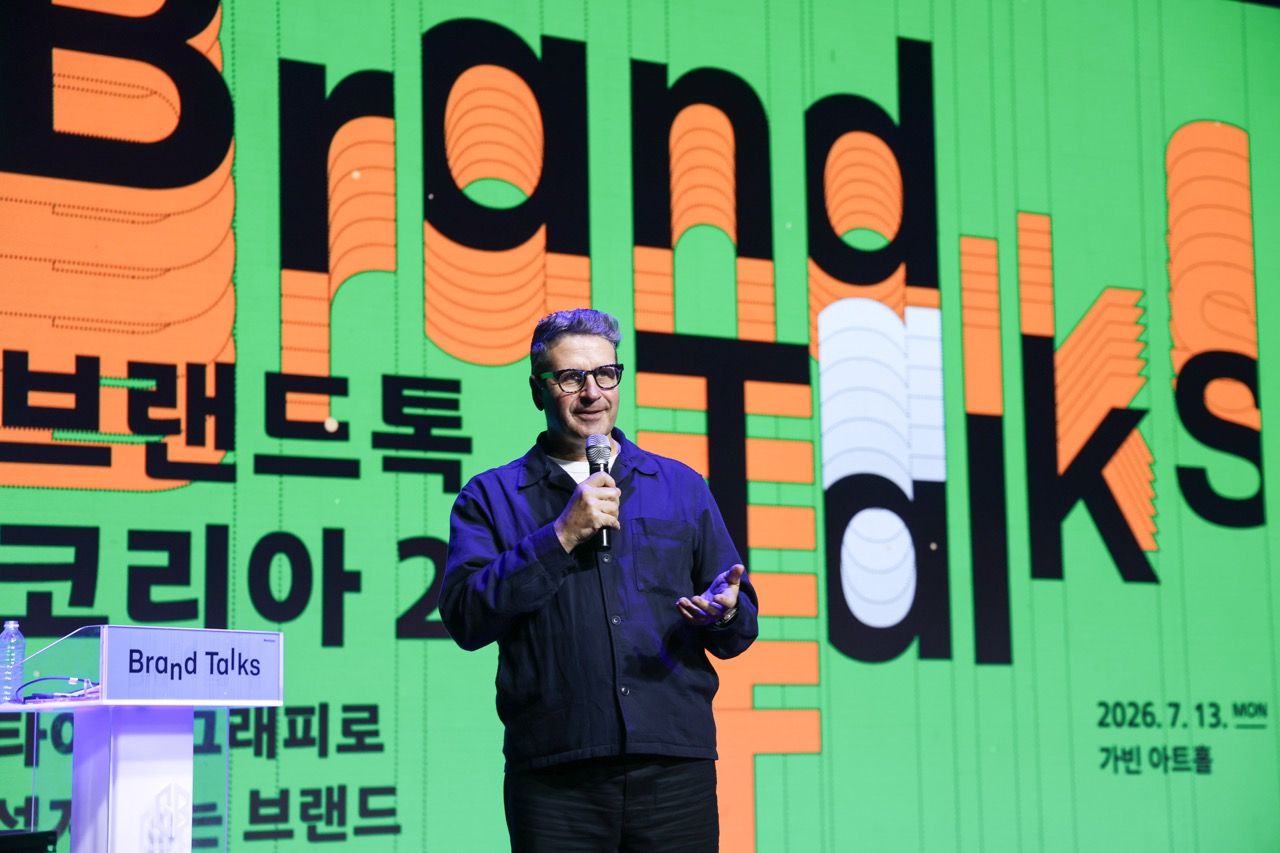
- 타이포그래피와 리브랜딩 사례 통해 브랜드 경험 설계의 방향 제시
모노타입은 지난 7월 13일 서울 가빈아트홀에서 개최한 ‘브랜드톡 코리아 2026(Brand Talks Korea 2026)’을 성황리에 마무리했다고 밝혔다.
올해로 3회째를 맞은 브랜드톡 코리아는 국내 브랜딩, 디자인, 마케팅 업계 관계자들과 타이포그래피의 가치와 가능성을 공유하기 위해 마련된 행사다. 올해 행사는 ‘타이포그래피로 설계하는 브랜드’를 주제로, 타이포그래피를 단순한 시각적 디자인 요소가 아닌 브랜드의 목소리와 경험을 만들고 지속시키는 핵심 시스템으로 조명했다.
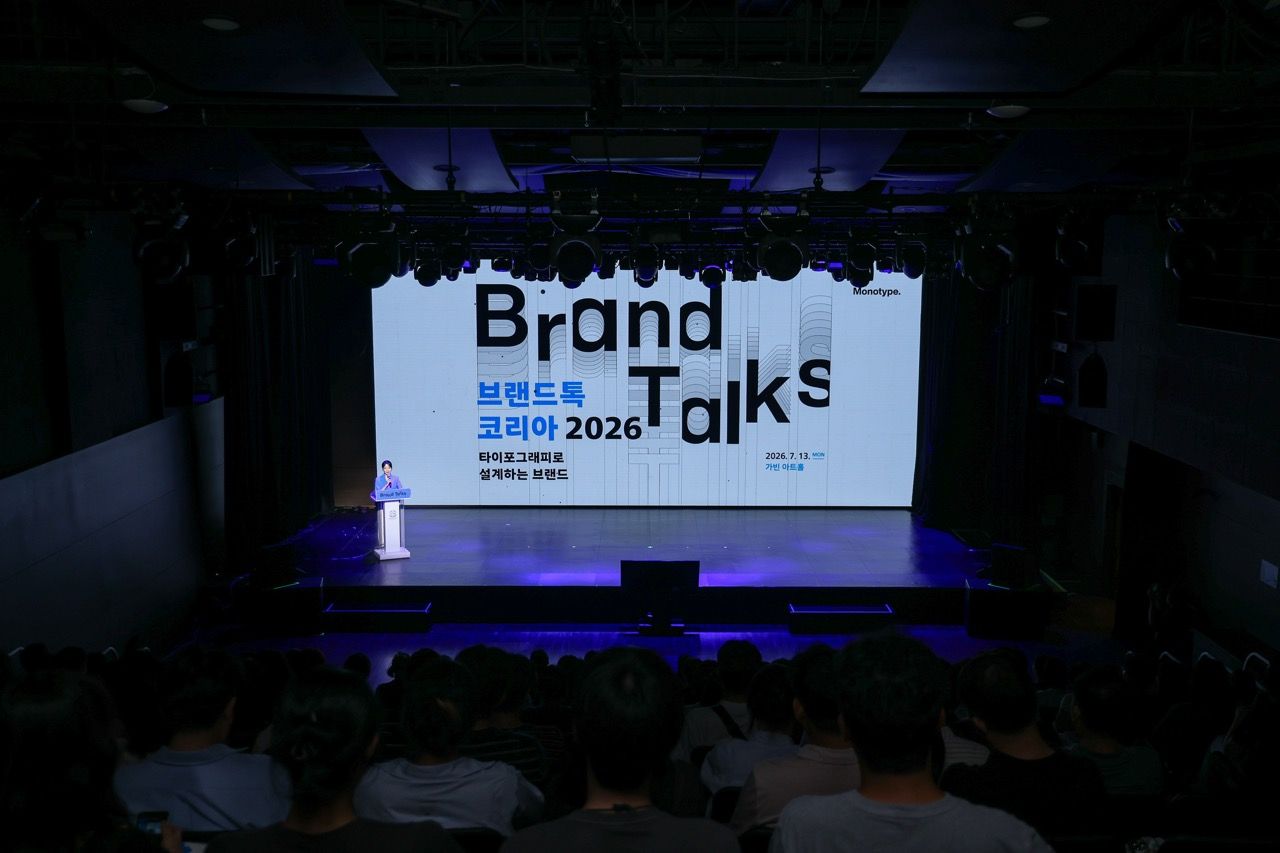
행사에는 모노타입 수석 크리에이티브 디렉터 찰스 닉스(Charles Nix)를 비롯해 김초롱 모노타입 크리에이티브 타입 디렉터, 장준호 인터브랜드 크리에이티브 디렉터가 연사로 참여했다. 세 연사는 타이포그래피 생태계, 전용서체 개발, 리브랜딩이라는 서로 다른 관점에서 브랜드의 정체성을 설계하고 일관된 경험으로 확장하는 방법을 소개했다.
첫 번째 세션을 맡은 찰스 닉스 디렉터는 타이포그래피를 하나의 ‘생태계’로 바라보는 관점을 제시했다. 폰트가 제작되고 배포된 뒤 조직에 도입돼 관리되고 실제 브랜드 접점에서 사용되는 전체 과정이 서로 연결돼 있다는 설명이다.
찰스 닉스 디렉터는 글로벌 브랜드가 다양한 지역과 조직, 플랫폼, 파트너 환경에서 일관된 목소리를 유지하기 위해서는 타입을 단순한 감성적 표현 수단이 아닌 운영 인프라로도 바라봐야 한다고 강조했다. 서체의 선택뿐 아니라 배포, 관리, 정책, 업무 흐름, 외부 파트너와의 협업까지 함께 설계해야 브랜드의 일관성과 신뢰를 지속할 수 있다는 것이다.
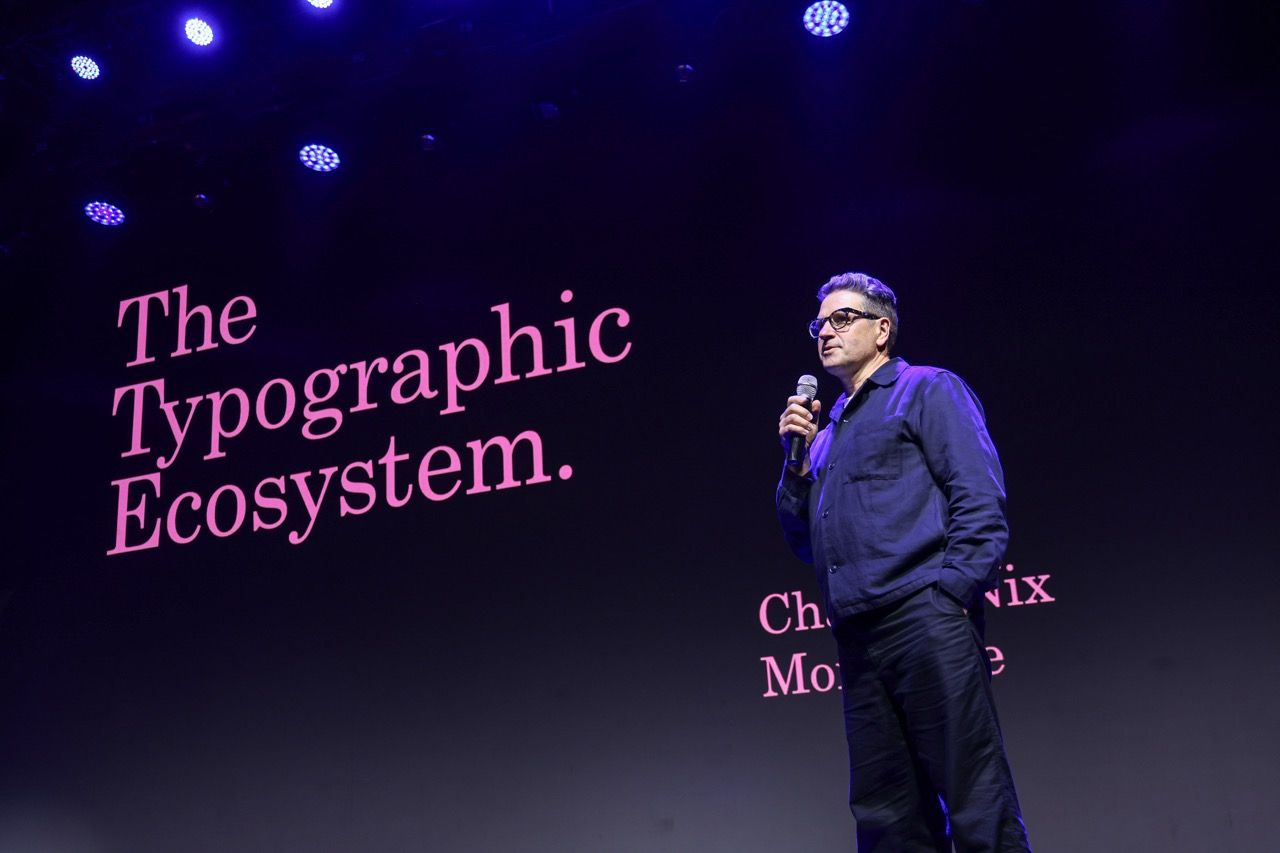
그는 일관성이 브랜드 정체성을 만들고, 정체성이 인지도를 높이며, 인지도가 신뢰와 성장으로 이어진다고 설명했다. 또한 브랜드가 성장할수록 어떤 폰트를 사용하는가뿐 아니라, 폰트를 누가 선택하고 어떻게 공유하며 어떤 기준으로 적용하고 관리하는지가 더욱 중요해진다고 짚었다.
이어 김초롱 디렉터는 모노타입과 삼성전자의 실제 전용서체 제작 프로젝트를 통해 브랜드의 정체성과 글로벌 사용 환경이 글자의 형태와 기능에 어떻게 반영되는지 소개했다. 기획부터 디자인, 검수, 언어 확장에 이르는 제작 과정을 살펴보며 대형 글로벌 브랜드를 위한 전용서체 개발의 복잡성과 중요성을 설명했다.
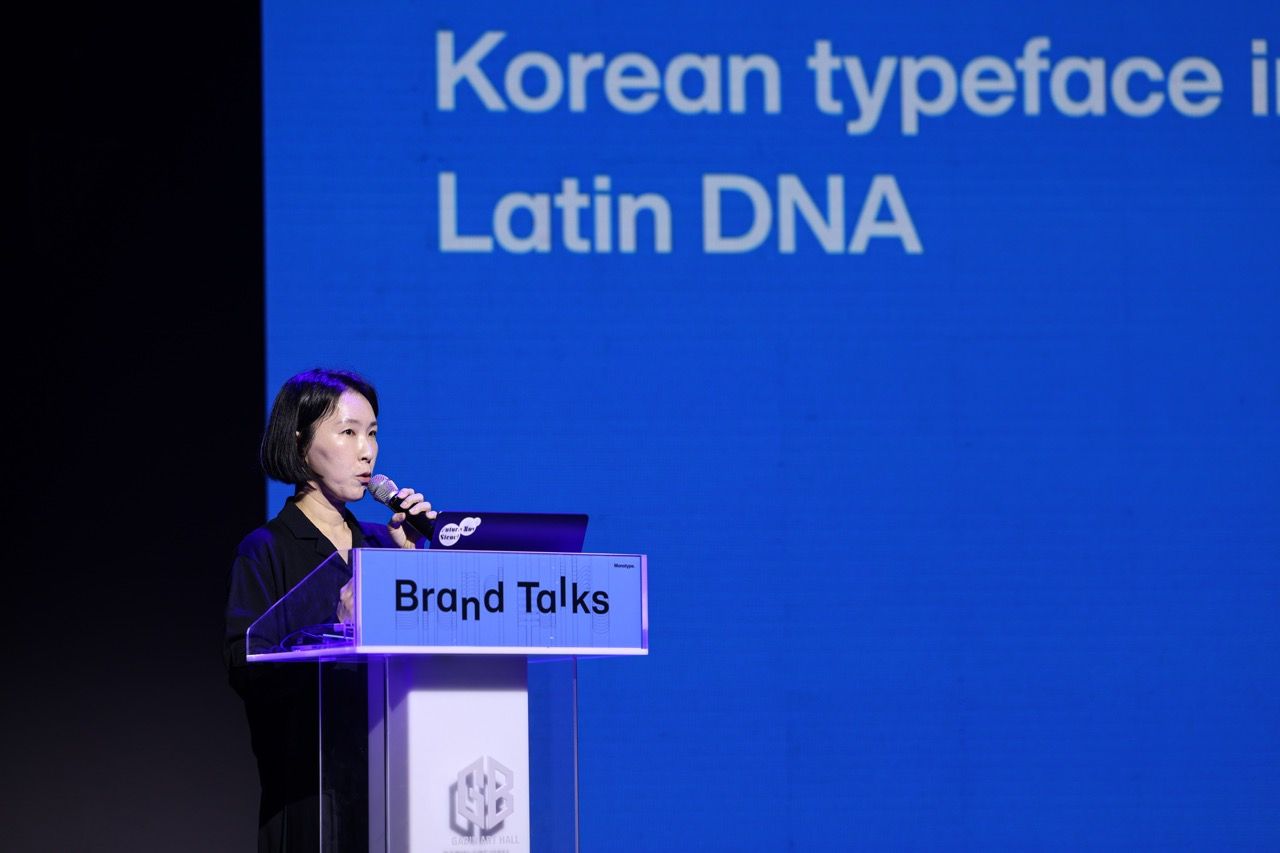
김초롱 디렉터는 전용서체가 단순히 브랜드의 개성을 시각적으로 표현하는 데 그치지 않고, 다양한 언어와 디지털 환경에서도 일관된 브랜드 경험을 제공하기 위한 시스템으로 작동한다고 강조했다. 브랜드 전략과 사용 목적을 글자의 구조와 세부 형태에 반영하는 과정도 실제 사례를 중심으로 공유했다.
마지막 세션을 맡은 장준호 디렉터는 서로 다른 배경과 과제를 가진 세 개 브랜드의 리브랜딩 프로젝트를 소개했다. 각 브랜드가 변화가 필요한 이유를 정의하고, 이를 새로운 전략과 시각 체계, 고객 경험으로 연결한 과정을 실제 사례를 통해 설명했다.
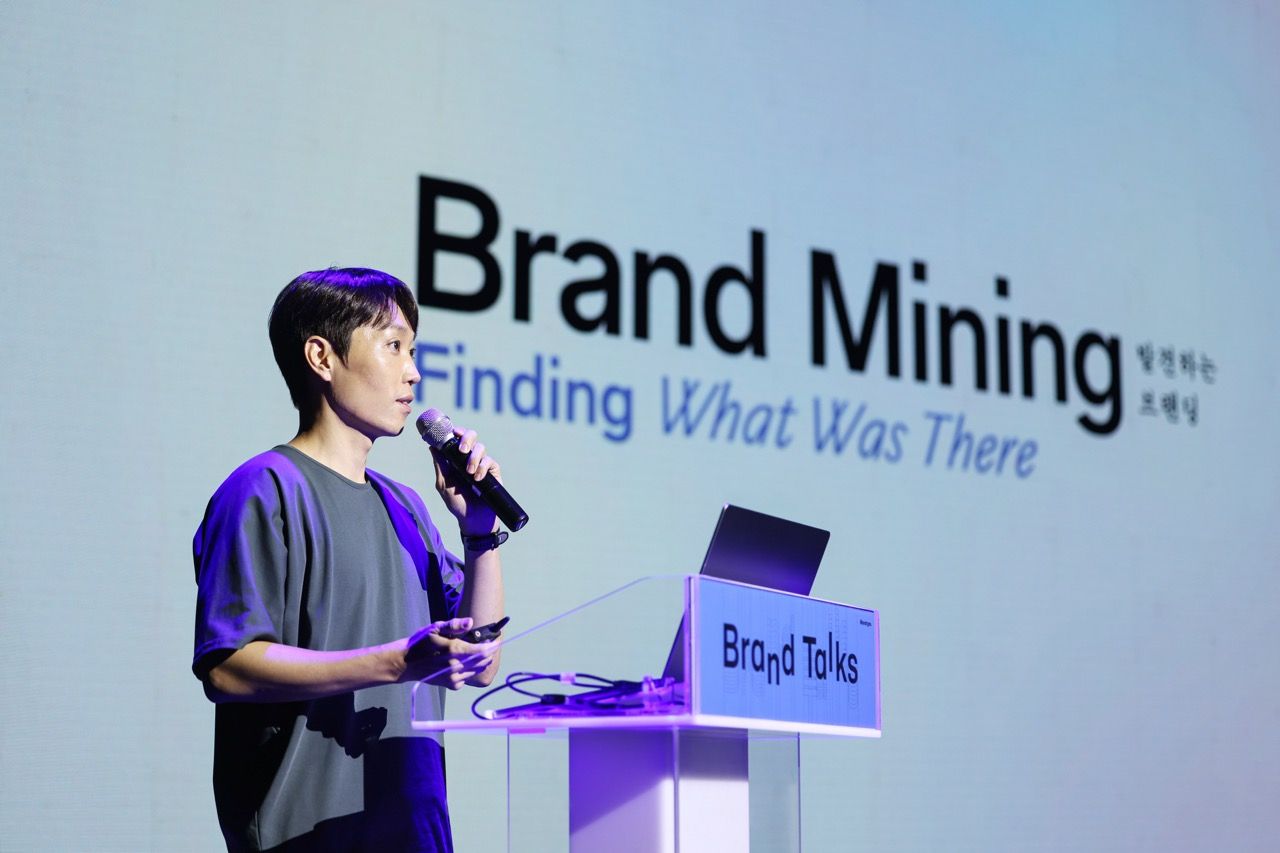
장준호 디렉터는 의미 있는 리브랜딩을 위해서는 외형을 새롭게 바꾸는 것보다 브랜드가 앞으로 어떤 역할을 해야 하는지 명확하게 정의하는 과정이 먼저 이뤄져야 한다고 강조했다. 또한 브랜드 전략이 로고나 그래픽에 머물지 않고 제품, 공간, 커뮤니케이션 등 여러 접점에서 일관된 경험으로 구현돼야 한다고 설명했다.
이번 행사는 타이포그래피, 전용서체, 리브랜딩이라는 세 가지 주제를 통해 브랜드의 정체성이 한 번의 디자인 작업으로 완성되는 것이 아니라는 점을 보여줬다. 브랜드다운 경험은 조직과 채널, 시장의 변화 속에서 지속적으로 설계되고 운영돼야 하며, 타이포그래피는 이를 연결하는 핵심 요소로 기능한다는 메시지다.
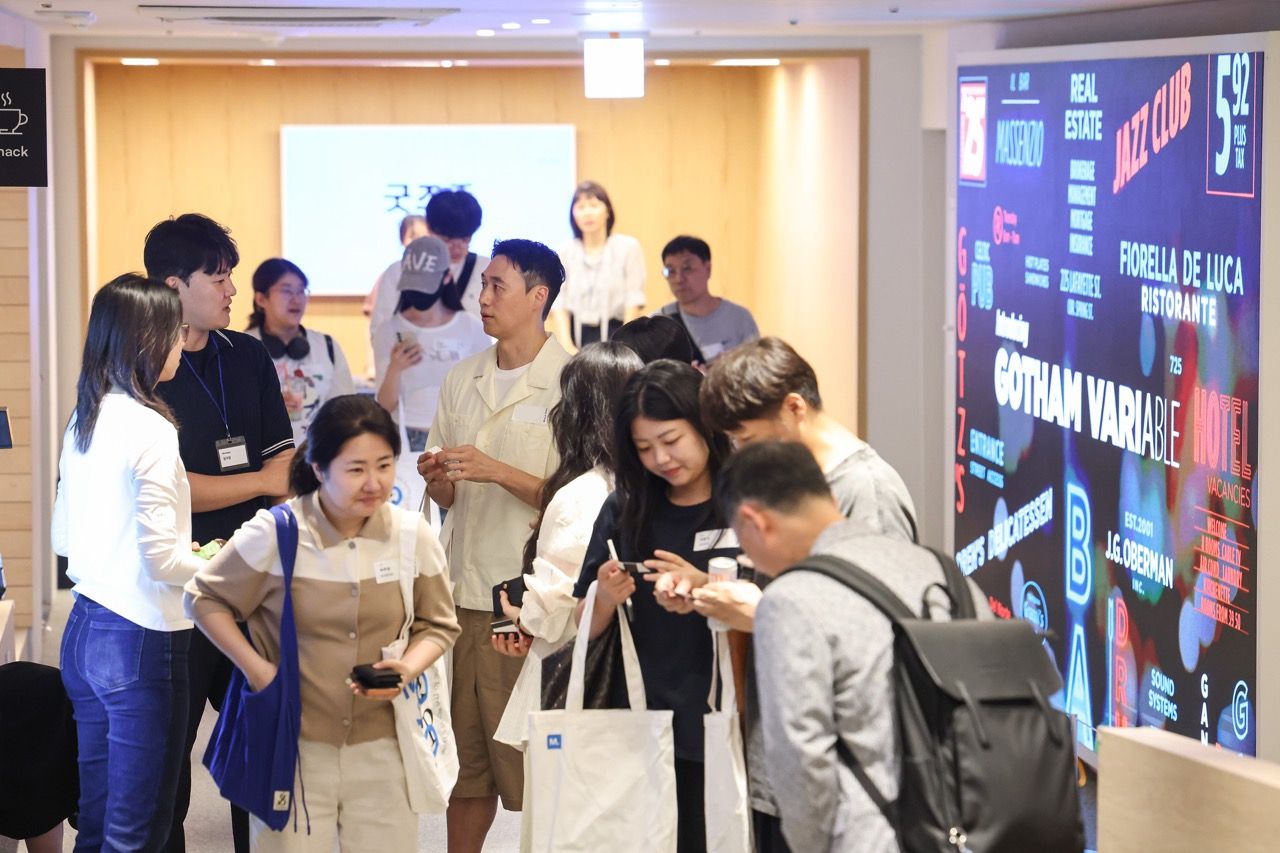
모노타입 김근원 시니어 마케팅 매니저는 “올해로 3회째를 맞은 브랜드톡 코리아는 타이포그래피가 브랜드와 비즈니스에서 갖는 중요성을 더 많은 사람에게 알리기 위해 이어온 행사”라며 “앞으로도 타이포그래피를 단순한 디자인 요소가 아니라 브랜드의 목소리와 경험을 만들고 지속시키는 기반으로 바라볼 수 있도록 의미 있는 논의를 이어가겠다”고 말했다.
모노타입은 향후에도 브랜드톡 코리아를 통해 국내 브랜드, 디자인, 마케팅 관계자들과 글로벌 타이포그래피 및 브랜딩 사례를 공유하고, 변화하는 환경 속에서 브랜드 경험을 효과적으로 설계하고 운영하기 위한 인사이트를 제공할 계획이다.